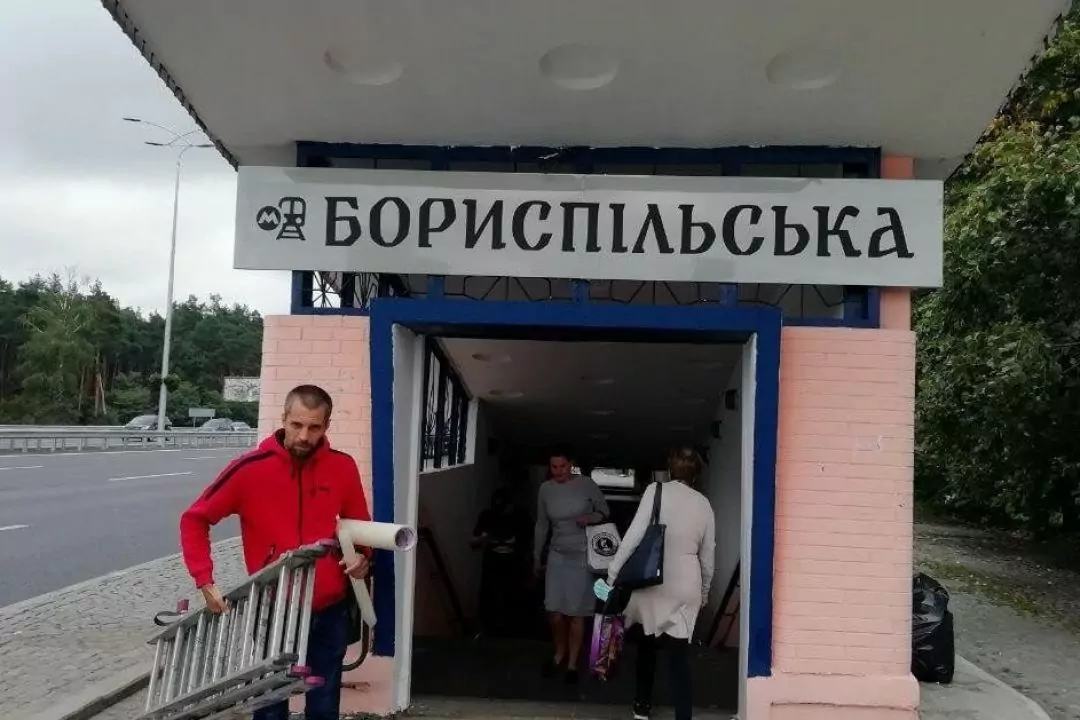
Київський дизайнер розробив новий шрифт для зупинок замість російського
Київський дизайнер Богдан Гдаль пропонує змінити російський шрифт «Іжиця» на зупинкових павільйонах України.
Як зазначає Гдаль,шрифт “Іжиця”, який використовують з початку 90-х, поширився Україною «за незнанням і через відсутність адекватних альтернатив».
Це шрифт, який розробила у 1988 році Світлана Єрмолаєва.
«Фактично це неправдивий новотвір з імперським духом та деякими рисами азійщини, якими Росія підмінила естетику Руси», – каже Гдаль.
Зверху – старий шрифт "Іжиця", знизу – розроблений Богданом Гдалем
За його словами, боротьбу з «Іжицею» він почав ще у 2020 році, але повномасштабна війна призупинила цей процес. Він підписав меморандум співпраці з «Укравтодором», а далі почав генерувати український шрифт на основі шрифту «Вернигора». Цей варіант погодили.
Шрифт, який розробив Богдан Гдаль
Поки що шрифт вдалося змінити лише на дорозі «Київ – Бориспіль».
Проте, було помічено, що компанія-виконавець знову замінила шрифт на «Іжицю» без узгодження макетів. Але після втручання міністерства шрифт виправили.
Шрифт, який розробив Богдан Гдаль
«Поки що ця дорога – єдине місце в Україні, де був свідомо змінений підхід до шрифту на зупинкових комплексах. У мене є свідчення, що на решті доріг тулять ту ж «Іжицю». Але я цю тему не кинув. Буду тиснути далі», – каже Богдан Гдаль.